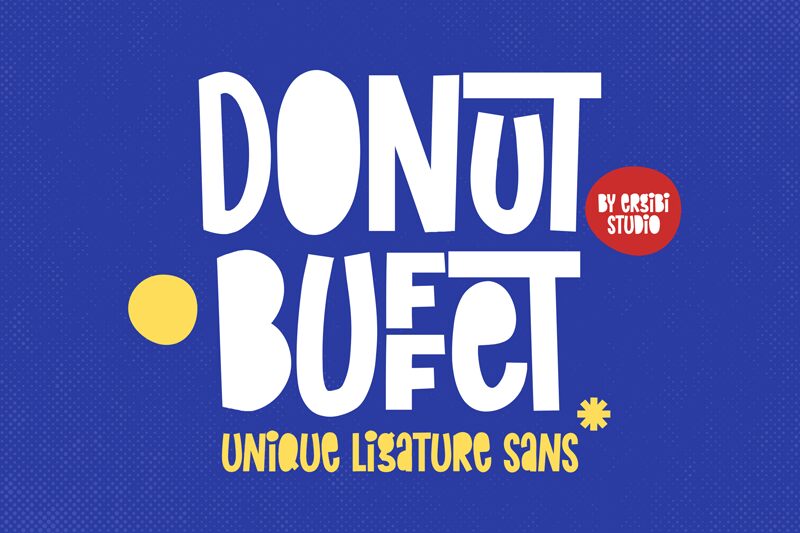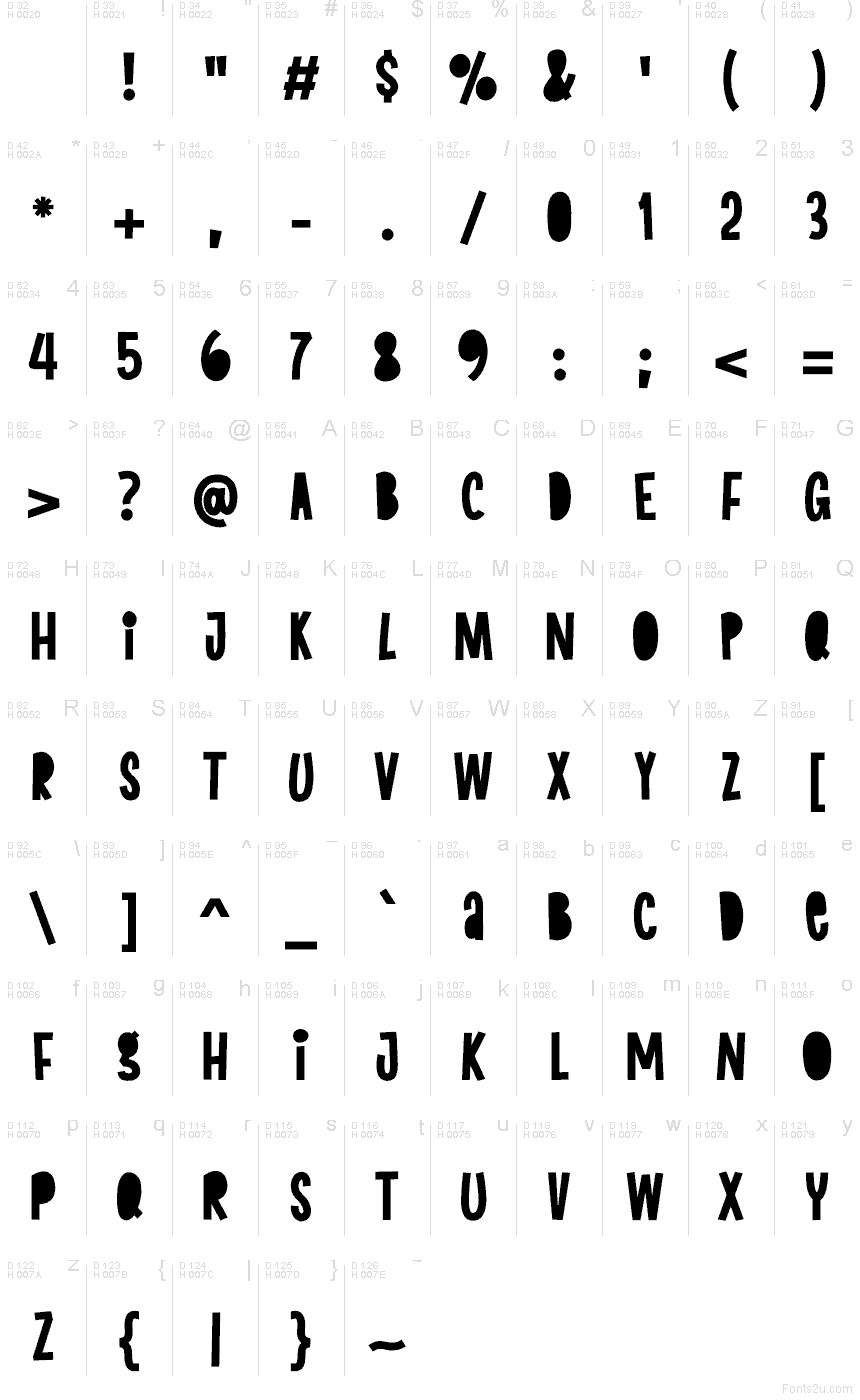
Donut Buffet, créée par ErgibiStudio, est une police de caractères ludique (type comic) dont les lettres semblent formées d'une pâte gonflée et moelleuse. Ses majuscules adoptent un rythme fantaisiste : les formes arrondies et larges côtoient des traits hauts et étroits. Ce côté irrégulier donne à la police un charme artisanal, évoquant les enseignes de snacks plutôt que le lissage propre aux dessins animés classiques.
Elle est idéale pour le packaging, l'identité visuelle de cafés, les invitations aux anniversaires d'enfants, les titres d'affiches ou les menus où cette police gratuite peut apporter une touche gourmande et amusante. Grâce à ses lettres volumineuses et simples, elle fonctionne également très bien pour des titres courts ou des logos nécessitant une présence amicale et imposante.